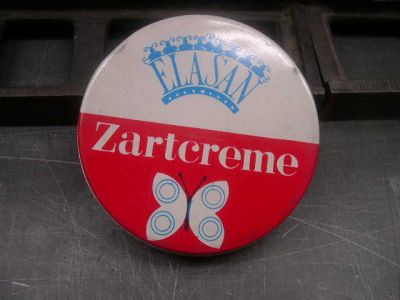
Eine typische Bleisetzerei aus Mitteldeutschland...
Da stand auf einer Banderole "Verinnerliche den internationalen Sozialismus". Das "inter" habe ich natürlich sofort weggekratzt.
Aber jetzt ist alles wieder gut. Lerne: Der Rheinländer frißt nichts auf lange Zeit in sich rein. Aller Mist kommt auf natürlichem Wege wieder heraus. Pffft...
Stammt sie aus den 60er oder den 70er Jahren?
Schlimmer noch. Ich glaube mich an sie zu erinnern. Also muss sie aus den Achtzigern sein.
für mich sind solche Daten immer ganz interessant, um herauszufinden, wann zuletzt mit diesem Bleisatz gearbeitet wurde.
In diesem Zusammenhang eine andere Frage an Euch Kollegen aus Mitteldeutschland:
Was für Photosatz-Systeme gab es in den 1980er Jahren bei Euch?
Was gab es überhaupt an Systemen? Hießen die nicht Robotronic oder so?
Die ist exakt von 1978, wie man an der Nummer auf der Rückseite sieht.
Also ist die Dose knapp 30 Jahre alt.
Und damit sie nicht so leer bleibt, schmeiße ich eine Handvoll Brotschrift-Lettern rein :)
Mir sind keine begegnet. Kann sein, daß es sowas bei der DEWAG (dem Werbebetrieb der DDR) gab. Ansonsten hat die DDR die Phase Photosatz wohl komplett übersprungen. Zumindest kann ich mich nicht erinnern, daß sie in der Lehrausbildung auch nur erwähnt worden wären. Im Ostblock wurden keine Systeme gefertigt und für den Import wird die Kohle gefehlt haben. Das, was man in der DDR-Öffentlichkeit an typographischer Vielfalt wahrnehmen konnte, war denn auch sehr eingeschränkt. Sehr, sehr eingeschränkt.
Ich war damals in einem graphischen Großbetrieb. Und jetzt halt Dich fest: Wir hatten die Kombination Offsetdruck und Bleisatz. Und das geht so: Man baut seine Druckform in Blei, dann geht diese zu einem geheimnisvollen Gerät, das Kugelvibrator heißt (nicht lachen!). In diesem wird ein gefärbtes Spezialpapier auf die Form gelegt, über dem dann Kugeln vibrieren und die Form auf dieses Papier abreiben (wahrscheinlich so ähnlich wie bei den Papierchen, die einem heute der Zahnarzt zwischen die Zähne schiebt, um Reibungsflächen zu finden) dann wird das ganze auf Film umkopiert. Geht natürlich nur für Einfarben-Geschichten. (Oh, oh. Ich hoffe, ich verrate jetzt nicht sozialistische Hochtechnologie an den Klassenfeind. Dafür gibt es sicher ein paar Jahre Bautzen.)
Ich war damals im wissenschaftlichen bzw. Formelsatz, da war man nur am fräsen und feilen, um recht komplexe Tabellen und Formeln in Blei zu basteln.
Der Rohsatz für den Formelsatz kam meist aus der Monotype, da hämmerten ein Stockwerk tiefer dutzende Monotype-Tast- und Gießmaschienen.
Die Lehrlinge nach mir wurden schon am Endlosperforator ausgebildet, das war ein Lochstreifenperforator, der an einer Art Computer hing. Von den Lochstreifen wurden Filme (Endlosspalten) belichtet, die dann manuell montiert wurden. Ging aber nur für glatten belletristischen Text, da waren wir im Blei flexibler. Ich hätte im 2. Lehrjahr auch zum Perforator gekonnt, habe mich aber fürs Blei entschieden.
Nehme ich gern an, weniger der Dose als der Lettern wegen.
Im Typoart-Buch »Fotosatzschriften« heißt es:
Der Einsatz von ausländischen Fotosatz-Computern in der polygrafischen Industrie der DDR erforderte auch die Übernahme von zugehörigen Fotosatzschriften, die nicht immer allen Anforderungen gerecht wurden.
Im Bestreben, überzeugende Schriftqualitäten zu erzielen, wurde im Jahre 1978 in der DDR der Entschluß gefaßt, die Entwicklung von Fotosatzschriften mit Hilfe einer Anlage zur geometrischen Datenverarbeitung im Betrieb Typoart Dresden aufzunehmen.
Wir haben also offenbar fleißig von Euch importiert.
Ist da jemals was zur Produktionsreife gelangt?
Na sicher doch.
Die Technik (Spitzname damals »Kugelfips«) ist hier im Film zu sehen, etwa ab Minute 12:05. Scheint ein DuPont-Patent gewesen zu sein und nicht, wie von mir oben angenommen, eine DDR-Eigenentwicklung. :aschehaupt: